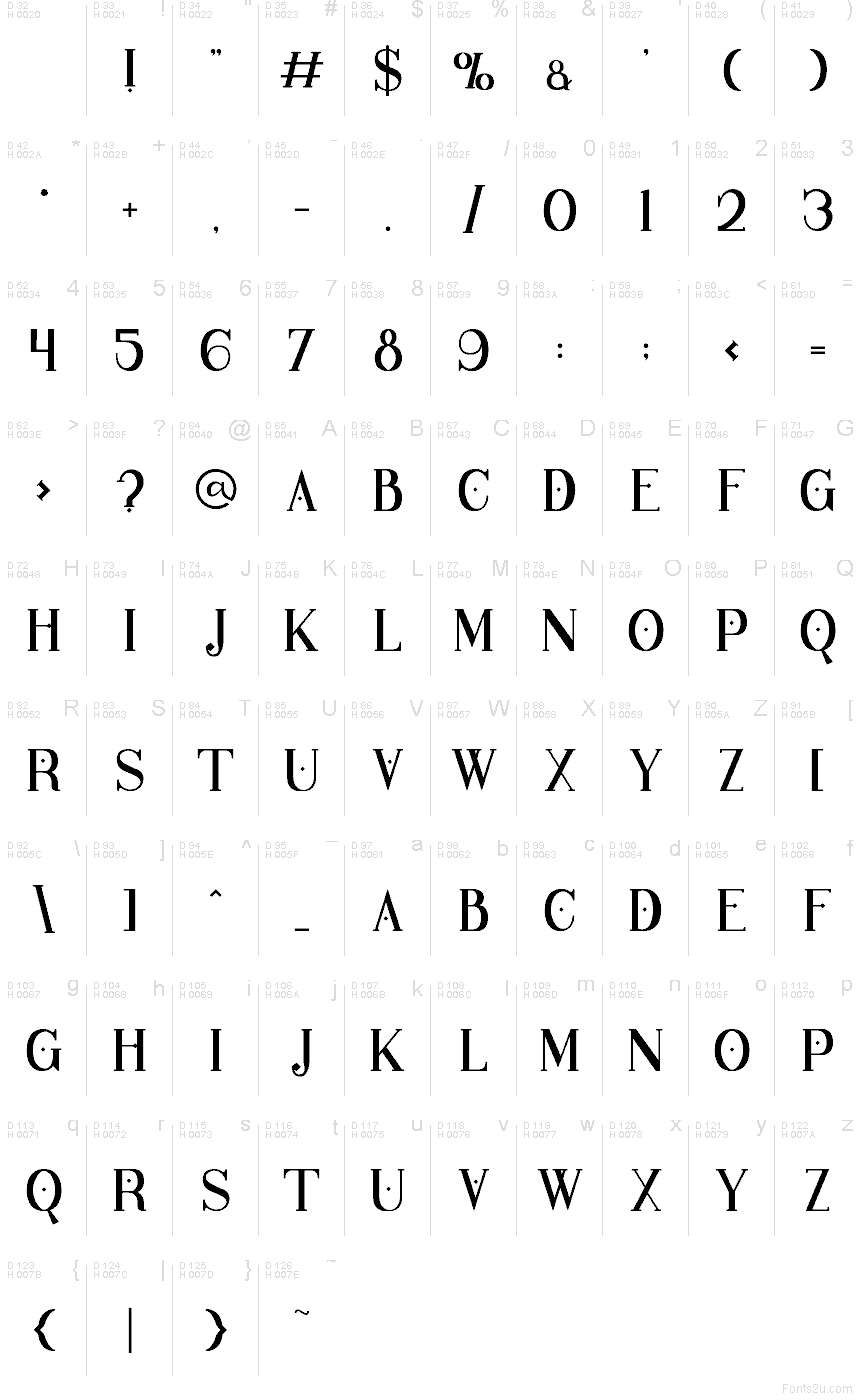
Pretty Satisfy Serif von Putracetol Studio ist eine dekorative Serifenschrift, die durch ihre markanten, rautenförmigen Einschnitte in den vertikalen Strichen besticht. Diese präzisen Details verleihen dem Schriftbild einen fast meißelartigen, juwelenbesetzten Rhythmus, während die klassische Serifengebung dafür sorgt, dass sie ihre Verankerung im gehobenen Display-Design behält, anstatt in bloße Spielerei abzudriften.
Die Schrift besitzt die nötige Ausstrahlung für Boutique-Logos, elegante Einladungstitel, hochwertige Kosmetikverpackungen, Menükarten oder redaktionelle Zitate, bei denen die facettierten Details visuell zur Geltung kommen. Durch die Mischung aus formeller Serif-Struktur und subtilen ornamentalen Akzenten wirkt jeder Text direkt veredelt, ganz ohne zusätzliche Verzierungen.